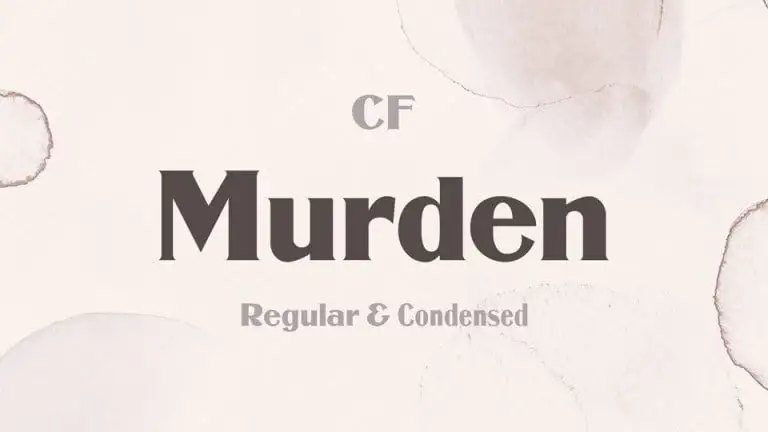
A Murden Serif é uma nova adição na categoria das fuentes serif para designers digitais apaixonados por linhas sólidas e elegância. Introduzida recentemente, esta font foi projetada pelo designer Chuck Mountain e está disponível para download no site da 99designs. A Murden apresenta um estilo forte e elegante, combinado com um toque delicado feminino que certamente transformará qualquer projeto de design em uma peça única e chamativa. Desenvolvida como uma reviravolta do Corbitt, um antigo tipo de caracteres encontrado no American Specimen Book of Type Styles da ATF (Jersey City, 1912), Nicholas J. Werner foi o criador original do Corbitt. O designer Chuck Mountain recuperou e redescobriu a beleza deste tipo de caracteres para criar a Murden Serif. Com um design meticuloso e uma estrutura sólida que promete destacar qualquer layout, esta font é perfeita para quem busca personalidade e sofisticação em seus projetos gráficos. Sua elegância extrema faz dela uma escolha ideal tanto para designers profissionais quanto para iniciantes que buscam adicionar um toque único a suas criações digitais.